Sáng bừng website với 45 font chữ cao cấp miễn phí (P.2)
Trong phần trước, chúng ta đã đến với những font chữ đẹp mắt dành cho thiết kế web. Nếu bạn chưa tìm được font chữ nào phù hợp với website của mình thì hy vọng bạn sẽ được hài lòng với phần tiếp theo này.
Bảng chữ cái đầy đủ cùng các ký tự thông dụng đi kèm. Bạn sẽ làm được rất nhiều việc có ích khi tải về bộ font chữ này. 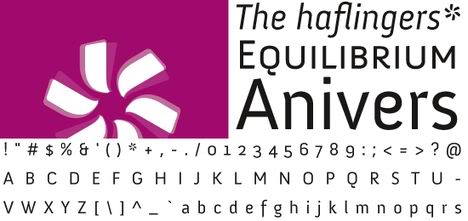
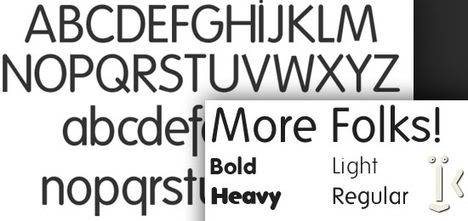
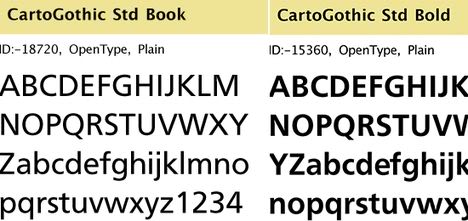
Một lựa chọn khá độc đáo và ấn tương cho dịch vụ thiết kế web của bạn. 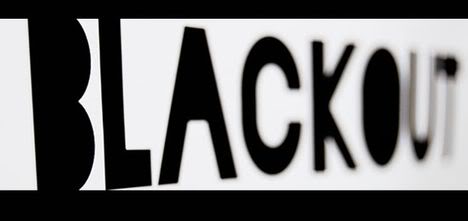
Font chữ hỗ trợ đa ngôn ngữ và hoàn toàn miễn phí tải về. 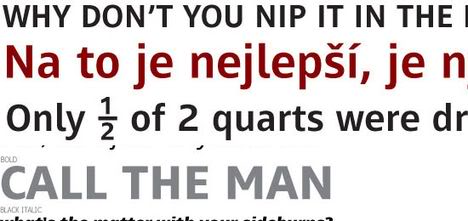
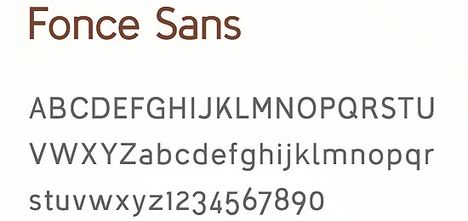
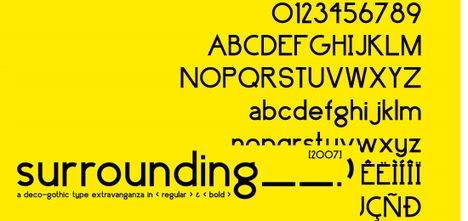
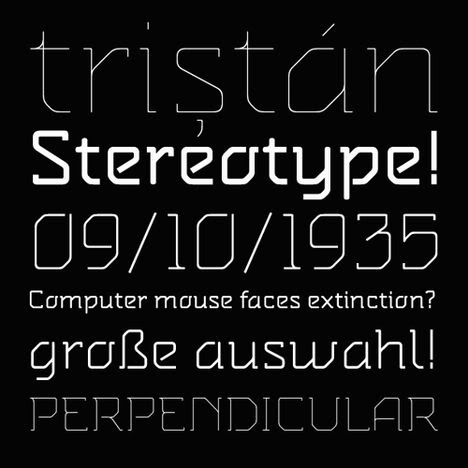
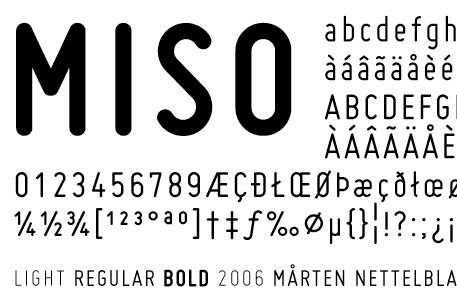
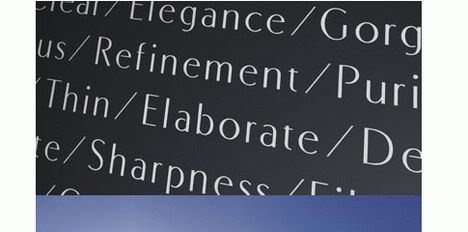
Resonance Bold
Với font chữ này, bạn sẽ có 2 lựa chọn: chữ đậm hơn với dòng kẻ bên trong và chữ thanh mảnh hơn không có dòng kẻ.
Atreyu lấy cảm hứng từ phong cách Gothic kinh điển thế kỷ 14. Đây là phong cách kiến trúc, trang trí có dấu ấn mạnh mẽ trong giới thiết kế nói chung và thiết kế đồ họa nói riêng. Mặc dù mang đậm chất cổ điển, nhưng với sự khéo léo kết hợp của các chuyên gia thiet ke web, chắc hẳn font chữ này sẽ được tỏa sáng trên các website hiện đại.